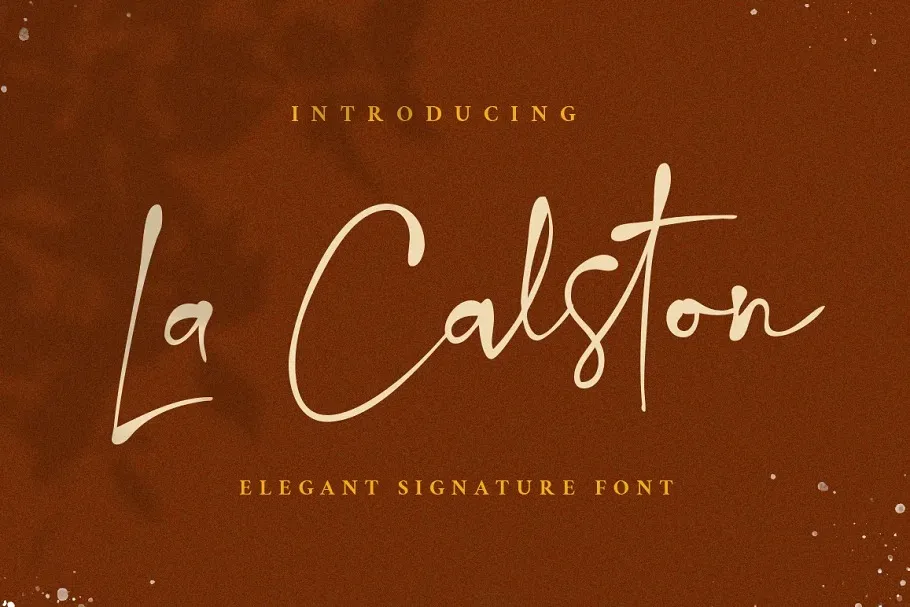
La Calston Font – Download Grátis
A La Calston Font é uma elegante e delicada fonte script criada para designers que buscam adicionar um toque único a seus projetos digitais. Inspirada nas cortesias luxuosas do mundo da moda, esta font representa o ideal da escrita manuscrita contemporânea, oferecendo ligaturas e estilos alternativos. Com seu charme único e sua sutileza inspiradora, La Calston é perfeita para aqueles que querem dar um toque sofisticado e inovador a qualquer design. Seja em uma marca de luxo ou na criação de um layout editorial moderno, esta font traz uma nova dimensão à sua proposta visual, garantindo sempre uma experiência singular. Não perca a oportunidade de incorporar o encanto da La Calston em seu próximo projeto.